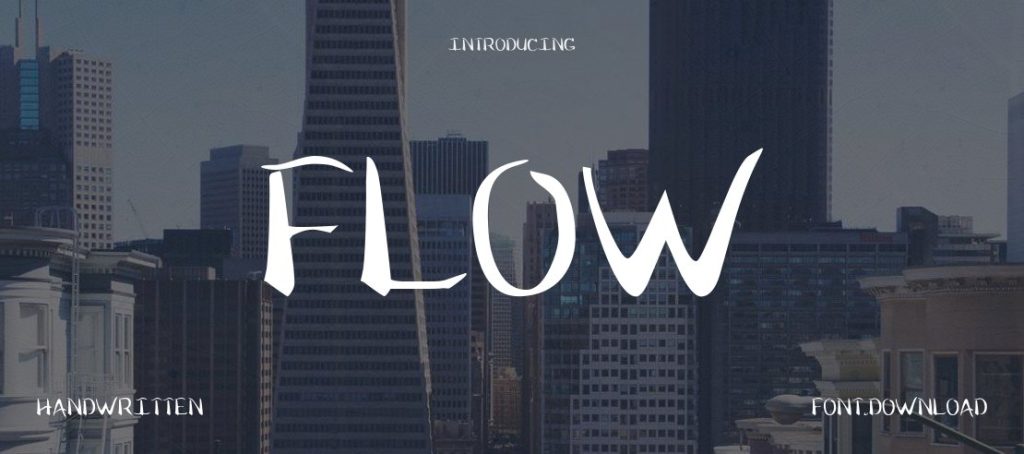
Flow Font được biết đến là một kiểu chữ hiện đại và độc đáo, mang đến sự mềm mại và linh hoạt cho thiết kế của bạn. Font chữ này thuộc font chữ design với các đường nét mượt mà và uyển chuyển, tạo ra cảm giác chuyển động và năng động, phù hợp cho các dự án cần sự sáng tạo và mới mẻ. Với khả năng tạo điểm nhấn và thu hút sự chú ý, Flow Font không chỉ giúp nội dung trở nên nổi bật mà còn góp phần truyền tải thông điệp một cách tinh tế, ấn tượng hơn và chúng thường được sử dụng trong các thiết kế liên quan đến thời trang, nghệ thuật.